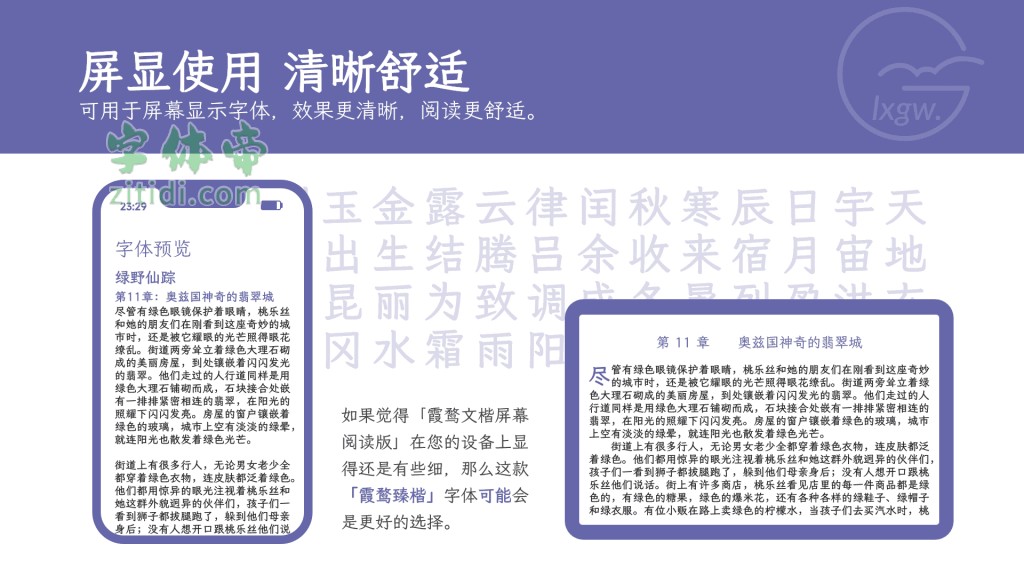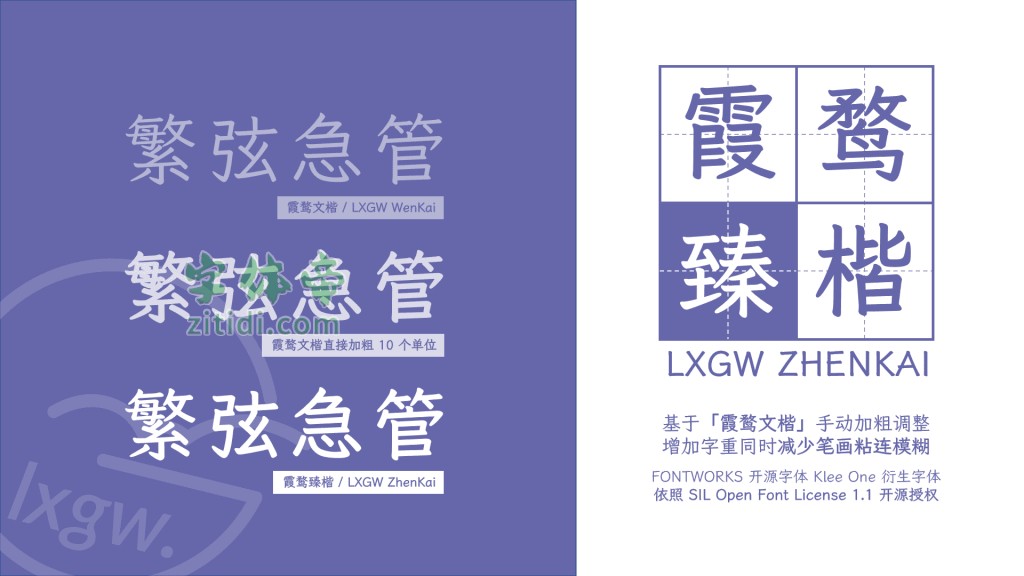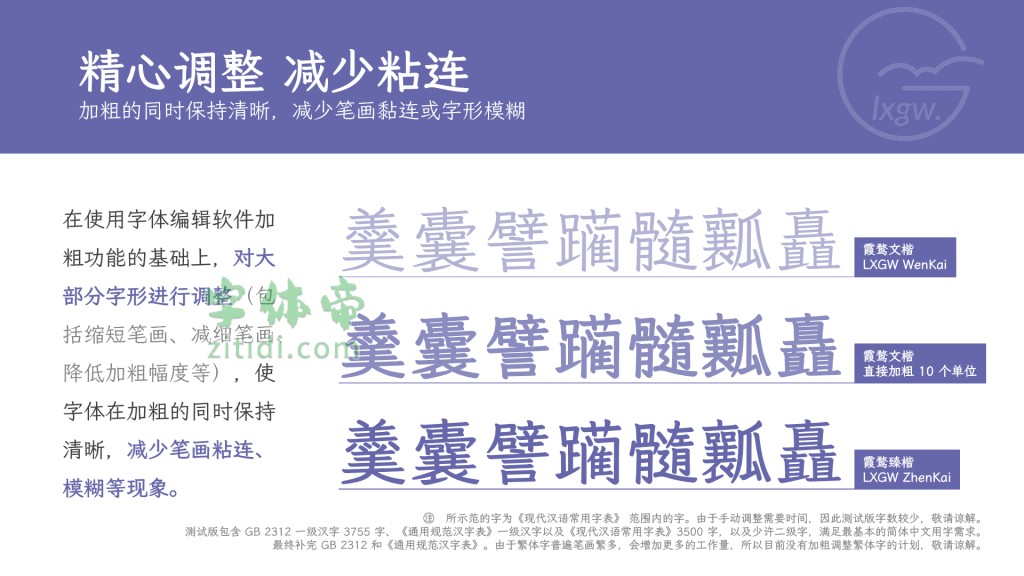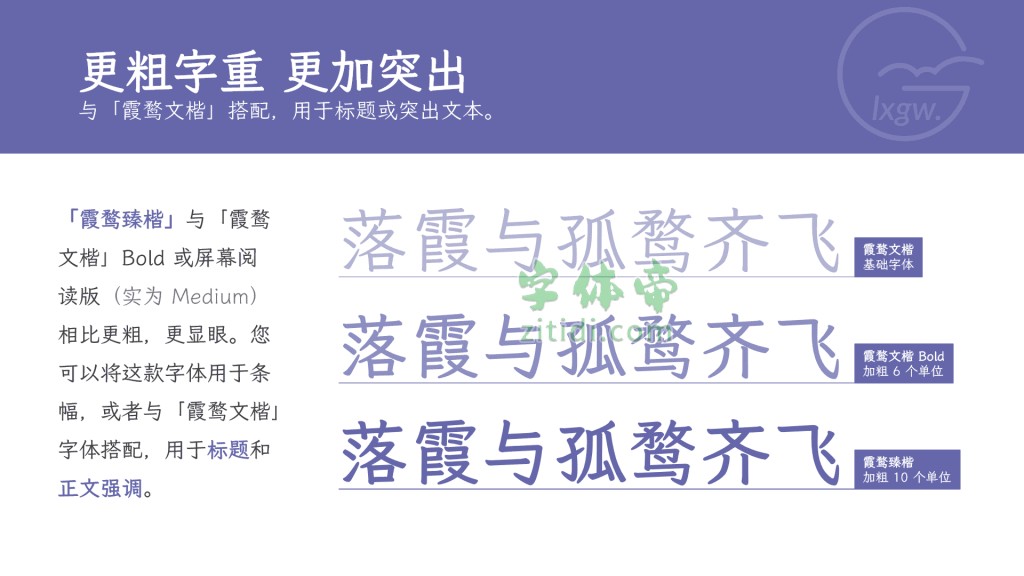
本字体是对 霞鹜文楷 / LXGW WenKai 粗字重的制作尝试。由于目前霞鹜文楷 Bold 字重(实为 Medium,也是「霞鹜文楷屏幕阅读版」 的常规字重)对部分用户来说依然比较细,且利用字体编辑软件的变换功能直接加粗的话,部分字形会糊成一片。因此开始了「霞鹜臻楷」这个项目,在使用字体编辑软件加粗功能的基础上,对大部分字形进行调整(包括缩短笔画、减细笔画、降低加粗幅度等),使字体在加粗的同时保持清晰,减少笔画黏连、模糊、毛刺等问题。
“霞鹜臻楷”是一款书写很新颖的字体,字体大方,适合各种设计作品使用!欢迎下载!